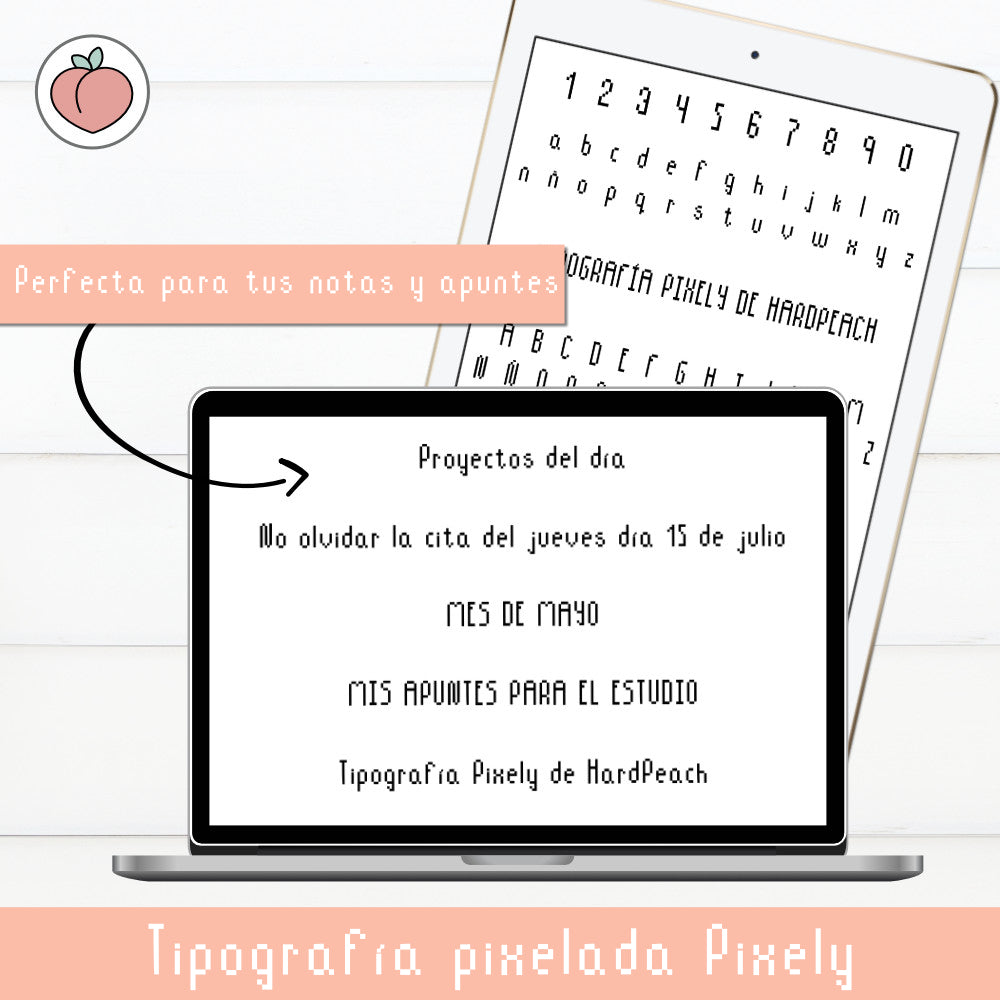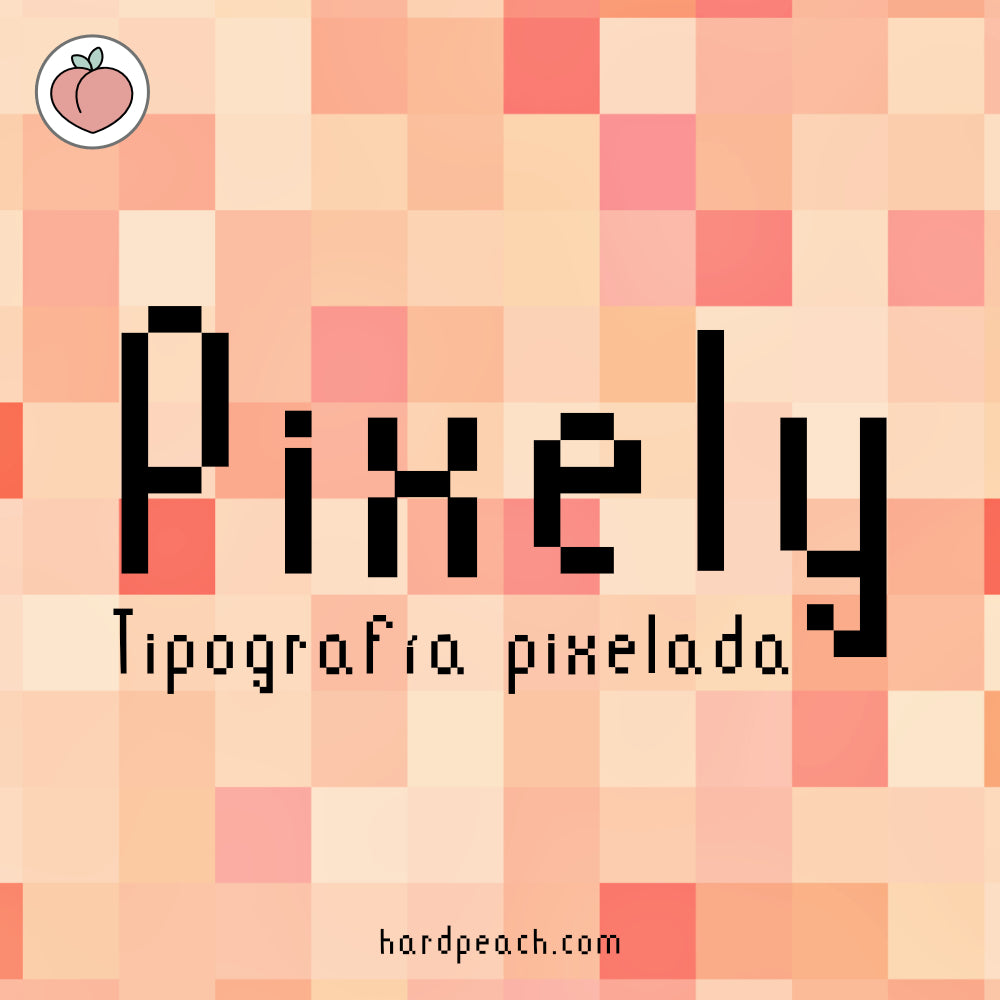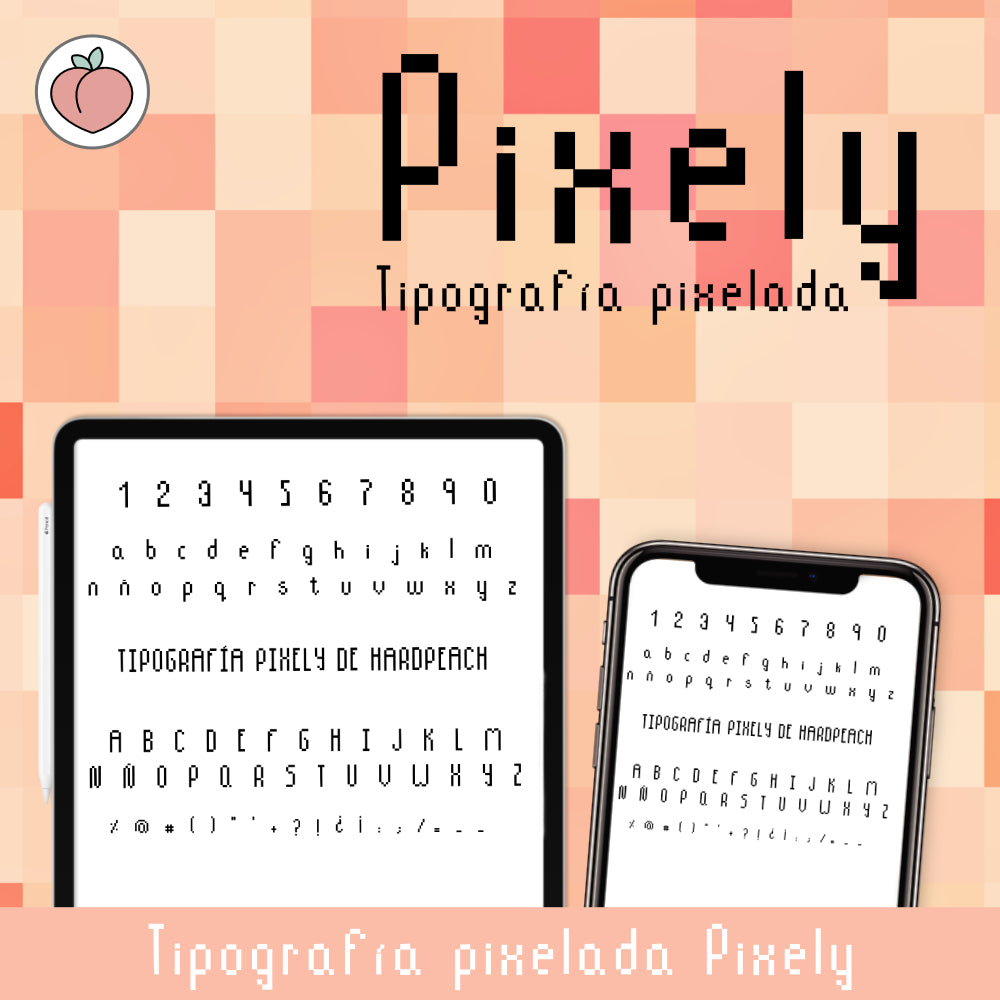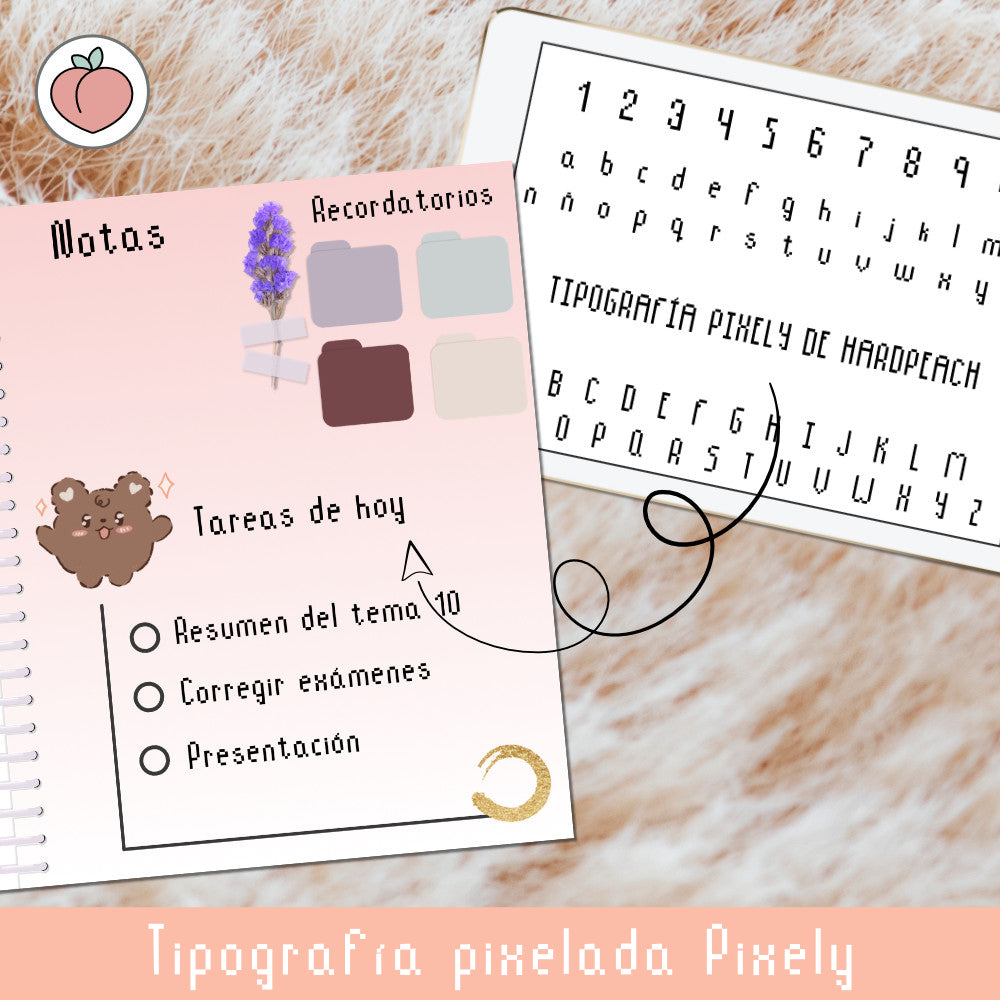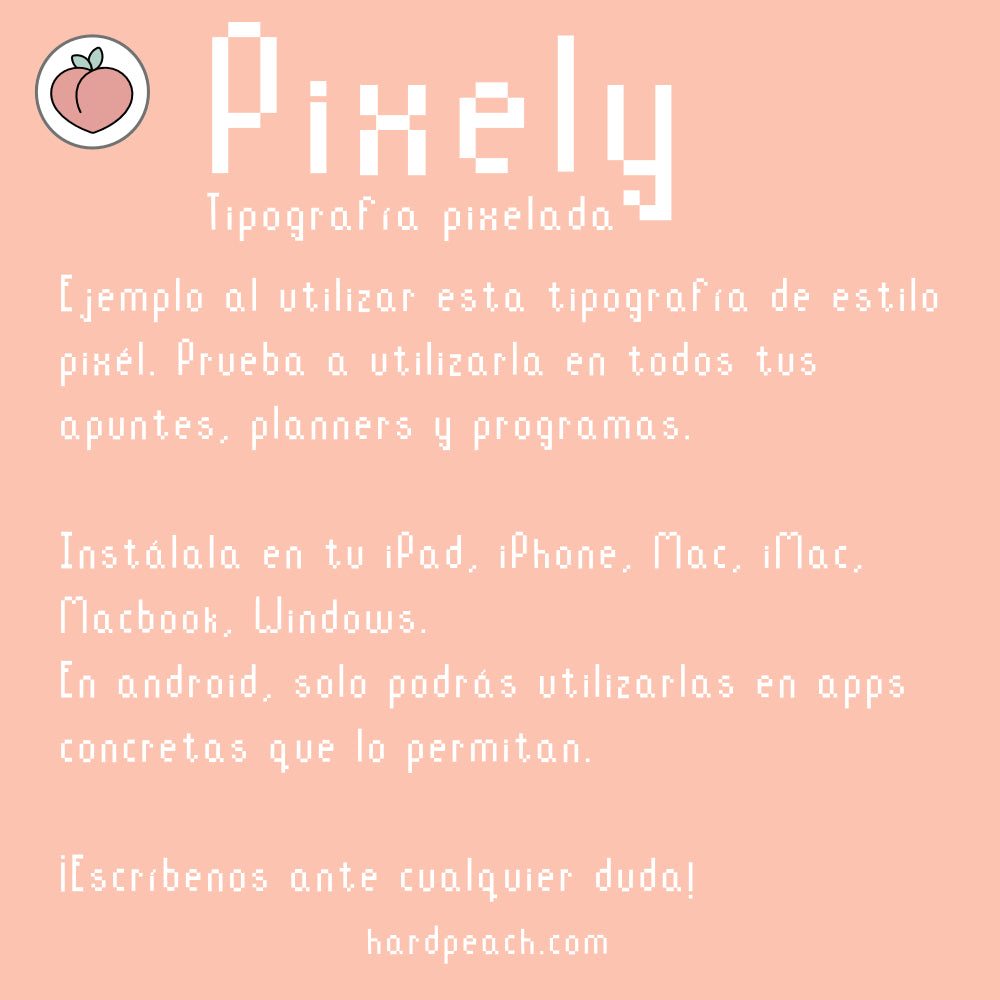
La tipografía Pixely combina un diseño pixelado único con máxima legibilidad, perfecta para apuntes, notas, esquemas, bullet journals, agendas, títulos y proyectos creativos. Su estilo retro-digital aporta un toque moderno y divertido a cualquier texto, haciendo que tus apuntes y diseños destaquen de manera original.
Incluye el alfabeto español completo, con mayúsculas, minúsculas, números, acentos y símbolos principales, ideal para todo tipo de escritura académica, profesional o creativa.
Pixely es ideal para estudiantes, creativos y profesionales que quieran dar un estilo distintivo y pixelado a sus apuntes digitales, presentaciones, proyectos gráficos o ilustraciones. Su diseño limpio y definido asegura que cada palabra se vea clara, organizada y con carácter.
Haz que tus apuntes, títulos y proyectos creativos luzcan únicos, divertidos y originales con la tipografía Pixely, combinando practicidad y estética en cada letra.
Esta tipografía está en Español incluye todos los caracteres principales, mayúsculas, minúsculas, números, vocales con tildes (español) y algunos signos esenciales. Al estar en Español, no incluye algunas acentuaciones de otros dialectos o idiomas.
Esta tipografía cuenta con los siguientes caracteres:
Abecedario de la A a la Z
Números del 0 al 9
Signos de puntuación más utilizados en Español
Signo de interrogación y exclamación
Incluye la versión estándar de la tipografía